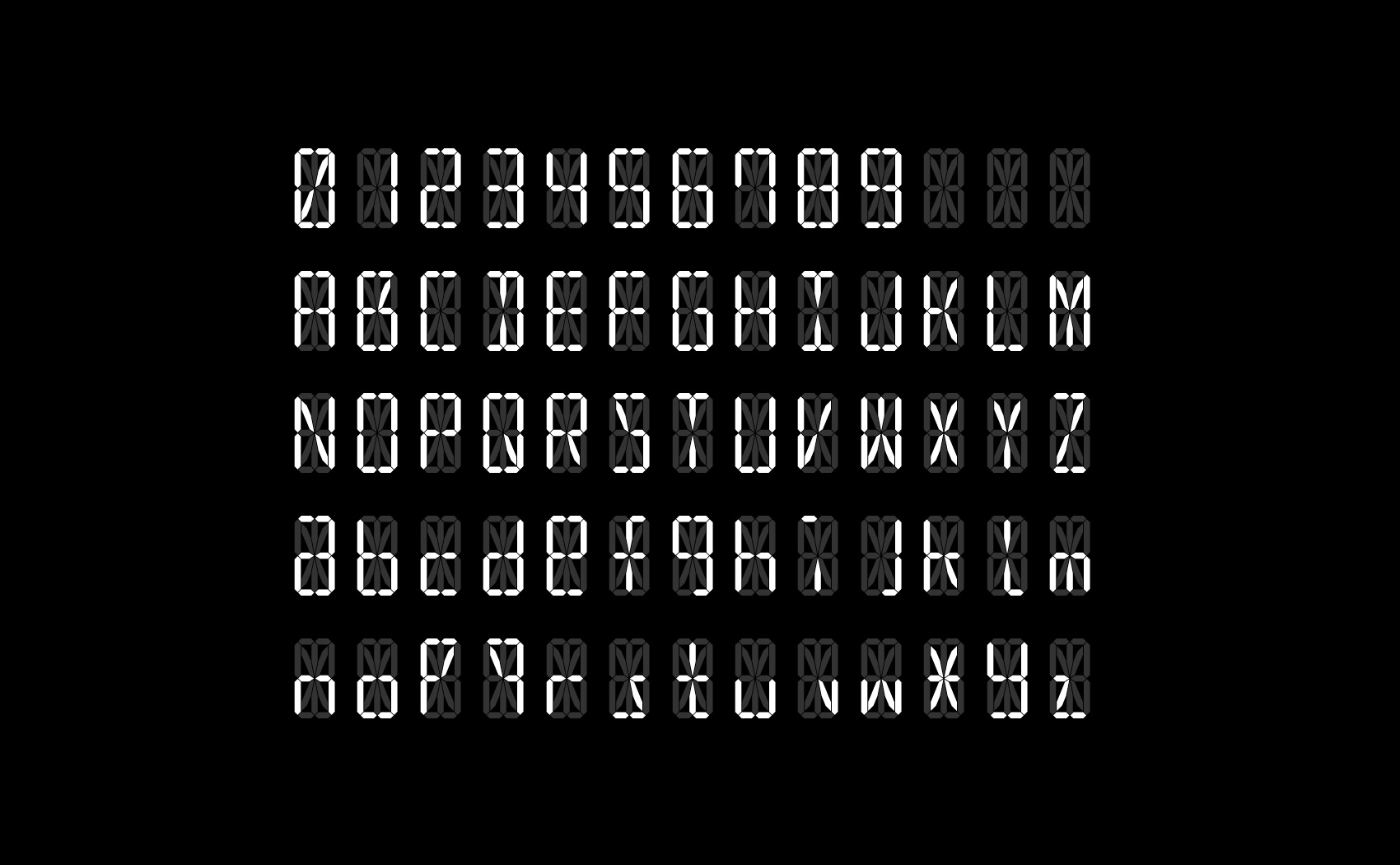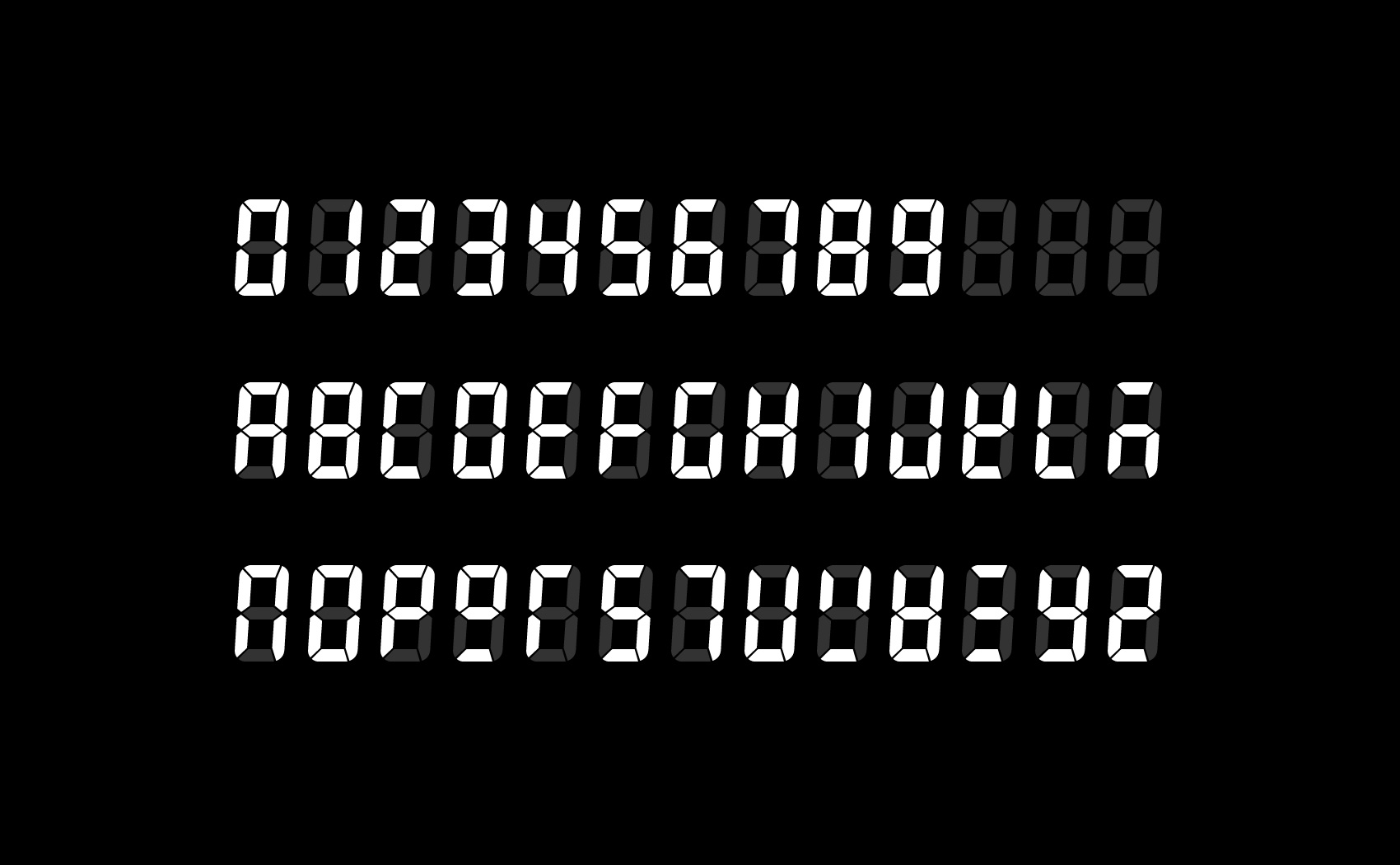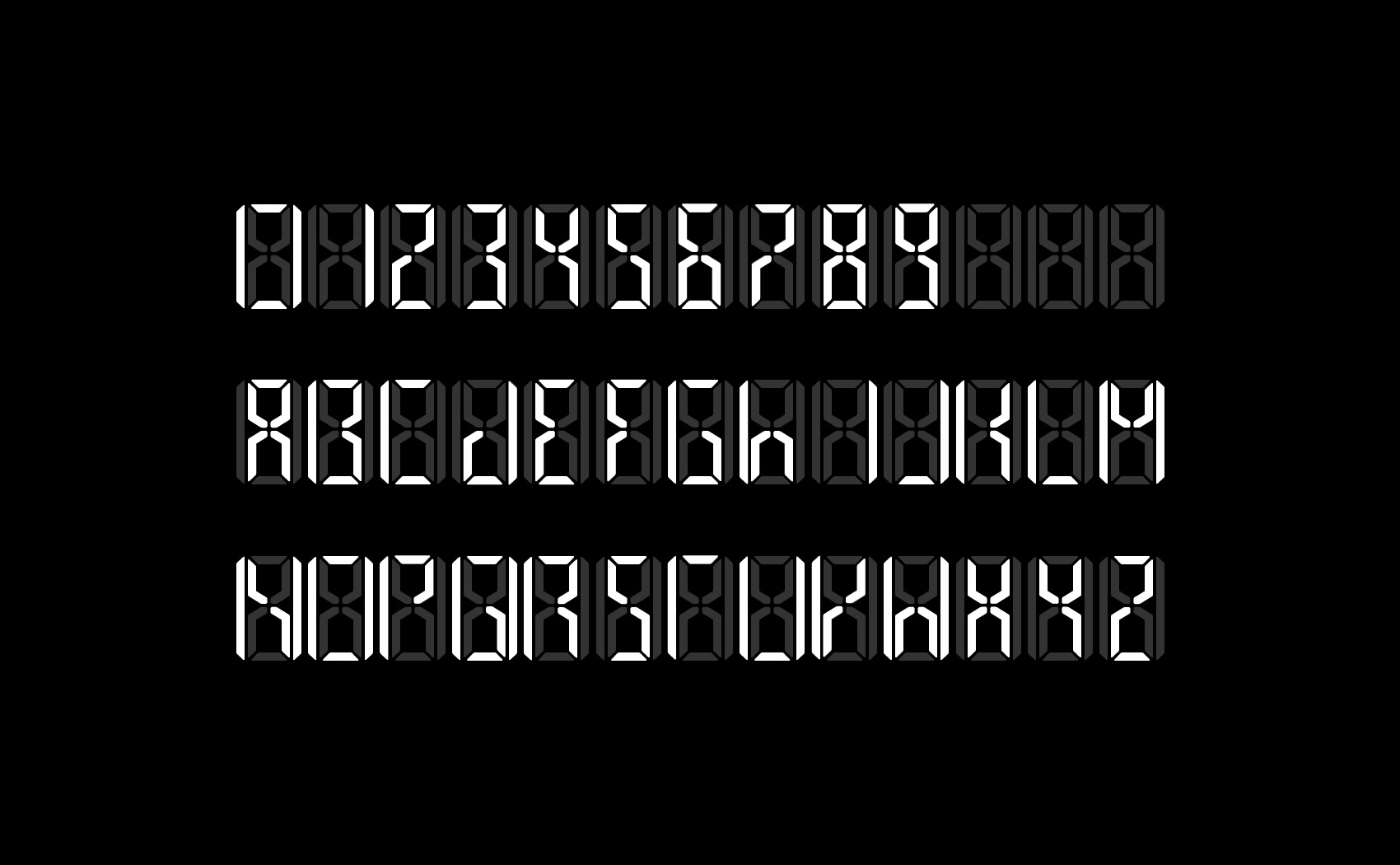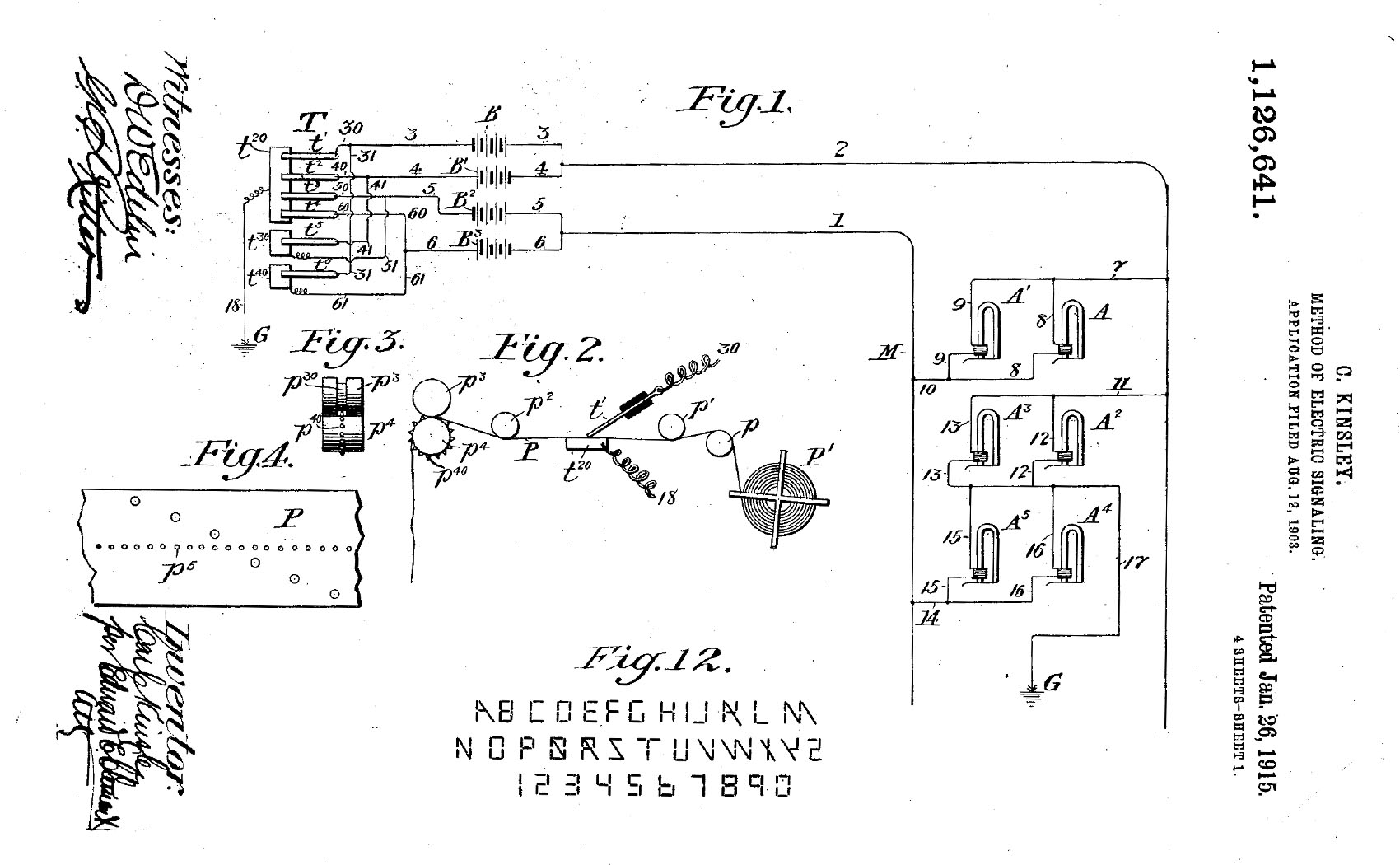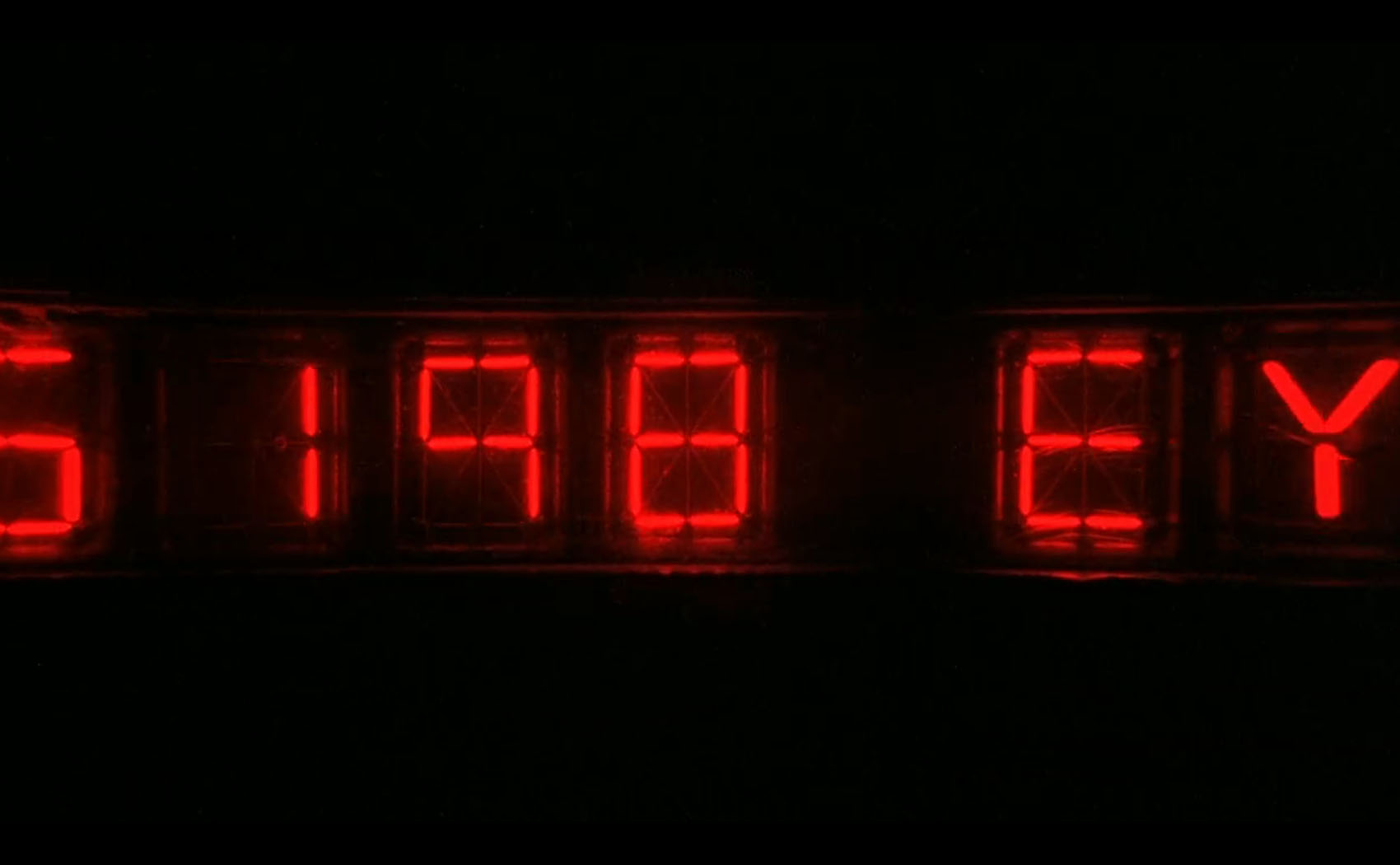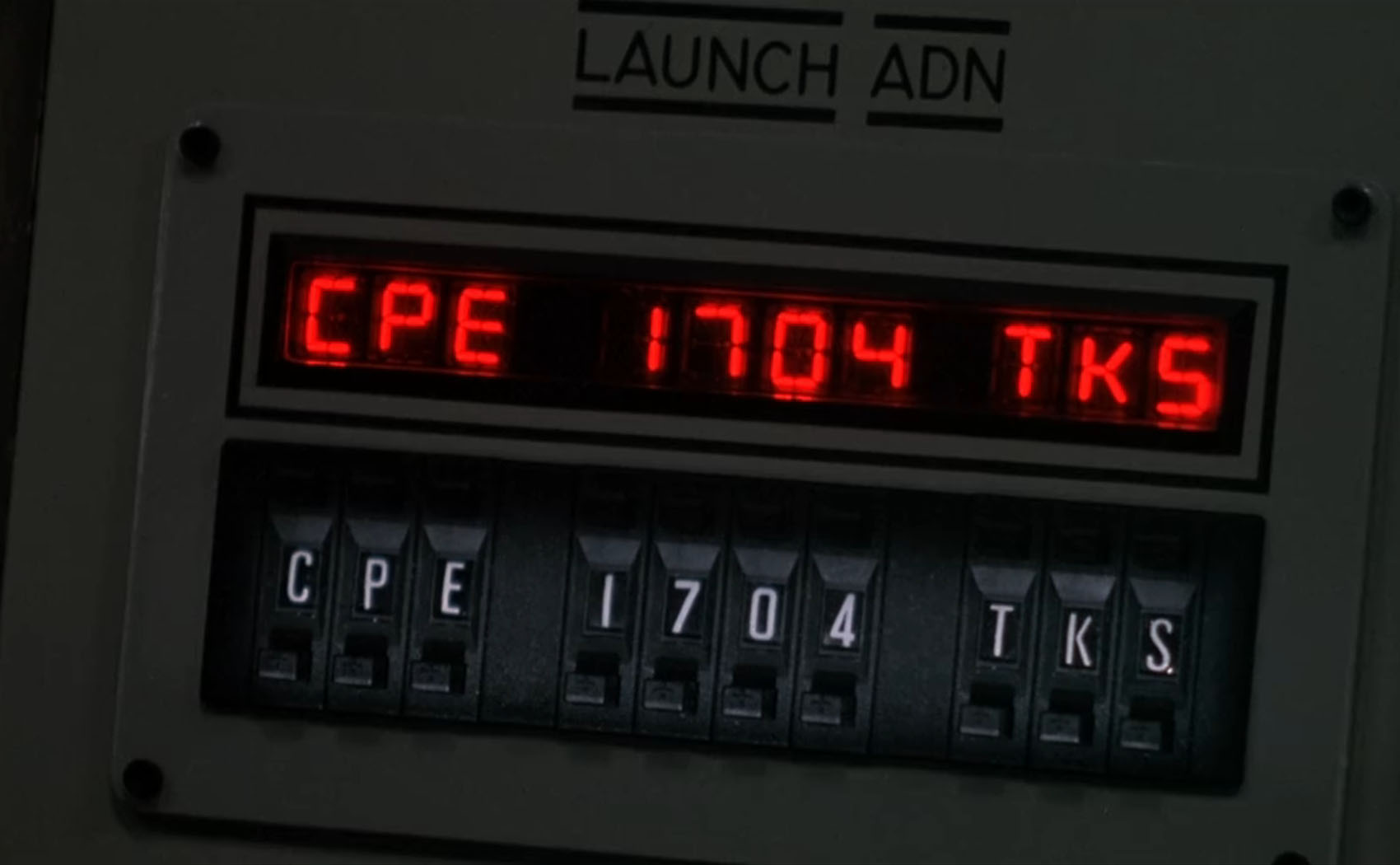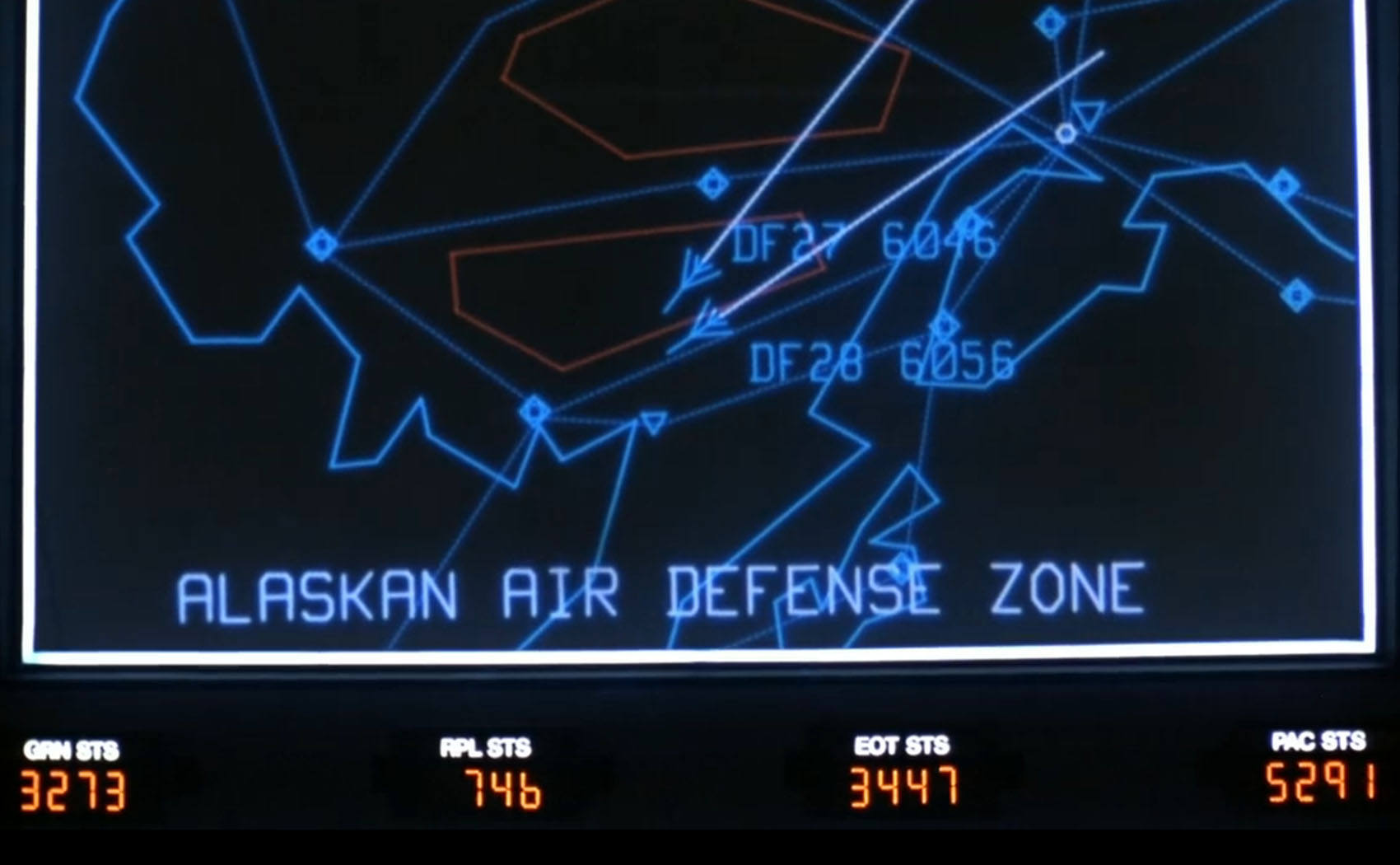
セグメントディスプレイ
「Wargames」の後半にAIの暴走がスピードアップするシーンで効果的につかわれるもう一つの文字スタイルがある。いわゆる「デジタル時計の数字」でお馴染みのセグメントディスプレイだ。
70年代以降、液晶やLEDのセグメントディスプレイは電卓や腕時計として家庭に普及していて、未来感をもった時代の進歩を感じることのできる馴染み深いアイテムであり、デジタル=セグメントディスプレイというほど現在に至るまでエレクトロニクスやコンピューター装置の可視化の記号として様々な演出に持ち込まれてきた。
日用品や普及品を用いて最大限にSF感を引き出すサバービアSFにとって、ひと目見てで何らかのシステムが動いていると認識でき、安価かつ確実に近未来のテクノロジー感を演出することのできる、このセグメントディスプレイは欠かすことのできないアイテムだ。特に有名なのは同じく80年代のサバービアSFの金字塔「バックトゥザ・フューチャー」のデロリアンのタイムサーキットだろう。民生品の組み合わせでタイムマシーンを作ることができるというこの時代ならではのありえそうな空想と現実と結びつける役目を果たしている。
「Wargames」での使われ方は、メインのスクリーン付近や、コンピューターターミナルの一部などに用いられ、ストーリーと関係する部分では、軍の核ミサイル発射装置の暗号をAIが解いていく際に、AIを表すベクター文字との対比で、ミサイル側の装置として赤いLEDの16セグメントディスプレイがつかわれている。
セグメントディスプレイの文字
セグメントディスプレイは科学技術の合理性に則して字形がつくられた技術由来の文字です。基本的な原理は、あらかじめ区画された7つの線の表示・非表示の組み合わせによってアラビア数字を表現する7セグメントにあります。電信などで数字を認識・表示する合理的な方法として1900年初頭に原理が発明され、1970年代にLEDの登場により普及しました。LEDのほかに、蛍光表示管(VFD:Vacuum Fluorescent Display)、液晶ディスプレイ(LCD)、近年ではドットマトリクスLCDなどで利用されています。
7セグメントは主にアラビア数字の表示が目的で、ドットマトリクスの普及までの間、セグメント数を増やしてアルファベットの表示文字を増加させる方法が試みられ、8、9、14、16セグメントなど表示文字の向上を試みていた時期があります。ドットマトリクスの登場でセグメントでの文字表現の追求は終焉を迎えましたが、数字の視認性の高さから多くの場面で数字の表示用の文字として現在も使われています。
7セグメント
7つ全てのセグメントを表示状態にすると数字の8となり、セグメントの表示・非表示の組み合わせで数字を表現する。基本的には数字の表示がメインだが、「ON・OFF」や「PLAY・STOP」などの操作の簡易表示に限られたアルファベット表現が用いられることもある。
ロシアン8セグメント
敵国側ソビエトの軍事関連でつかわれていた風変わりな8セグメント。数字・アルファベットとキリル文字を表示することができる。直線と短い斜線の組み合わせで少ないセグメント数でMやW、K、Xの表現が比較的認識しやすい。
16セグメント
7セグメントを基本に縦の中心分割線とX状の斜線が追加された14セグメントからさらに3本の横線を分割させ16セグメント。ラテンアルファベットの大文字・小文字の表示を目的に作られた。組込システムなどのディスプレイに利用されていた。映画の核施設で利用されていたのがこのスタイル。
セグメントディスプレイは、完全に技術由来の字形のため、数字の表現に関しては数理的に整って感じるのですが、アルファベットを表示させた場合、どうしてもバランスが悪く違和感がとても強くなります。そしてそれは、まるで機械とコミュニケーションをとるための暗号のような存在として長らく人々に苦労を敷いていました。90年代くらいまでのビデオデッキやCDプレーヤーなどのセグメントディスプレイをつかった設定は、現在のような考えられたUIの時代とは比べ物にならないほど不自由ですが、その不自由さは時代を経てしだいに哀愁をさそう存在になってゆきます。不自由さこそが、忘れられた時代に愛しさに変わってゆく。それがエレクトロニクスにおけるノスタルジーの原点なのかもしれません。